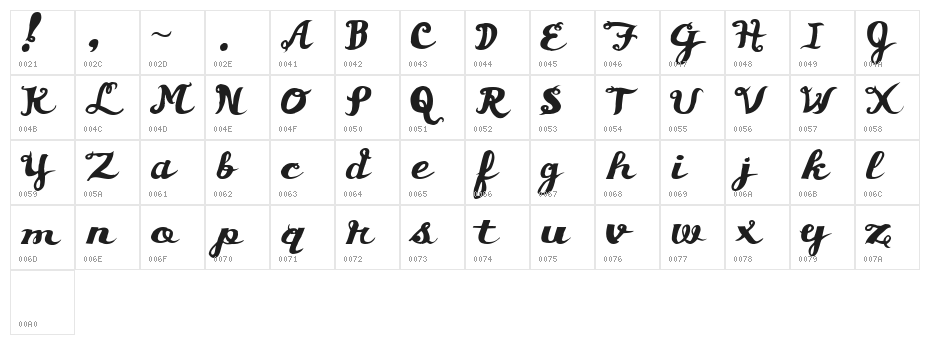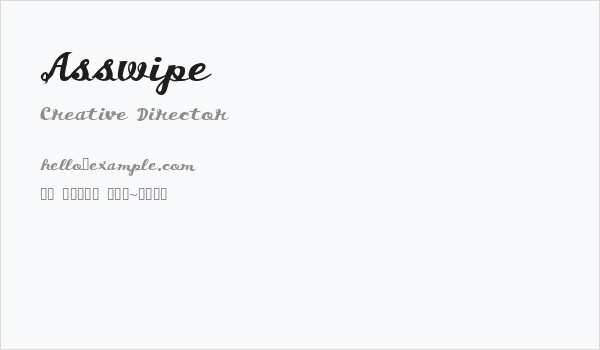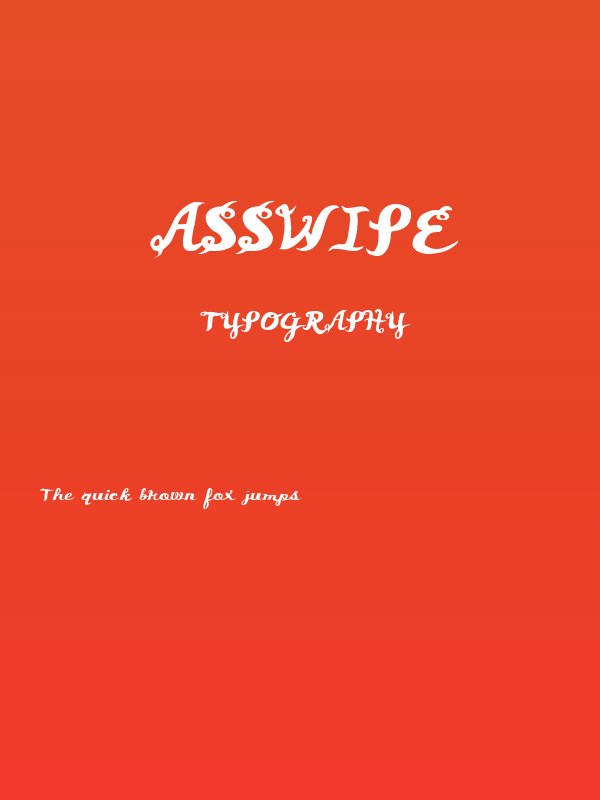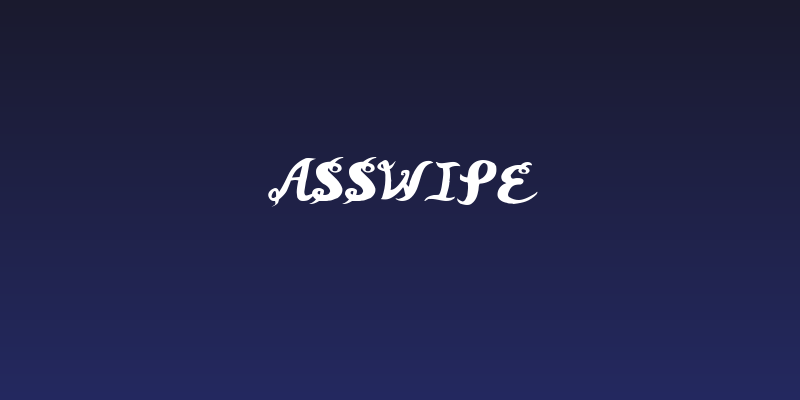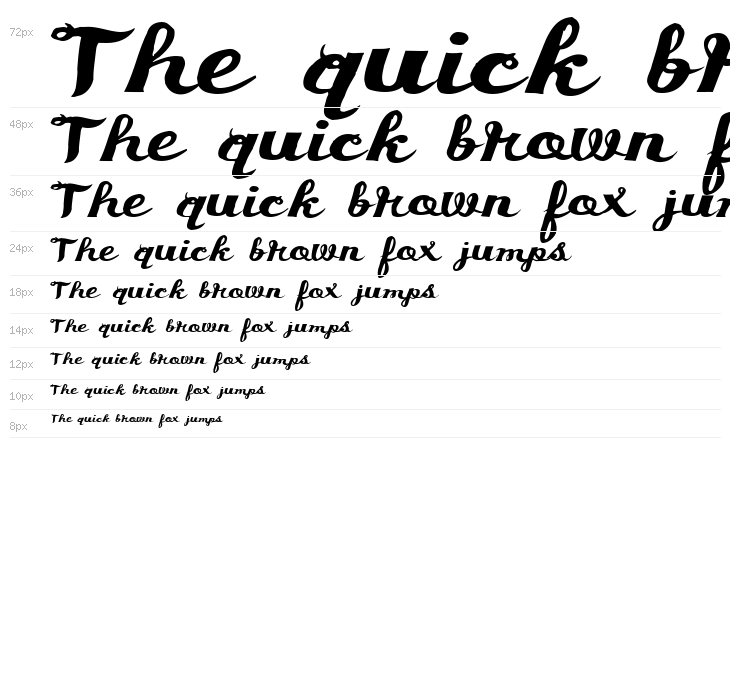
Asswipe Font
| Caso d'uso | Logos, Invitations, Decorative headings |
| Progetti proposti | Ideal for wedding invitations, formal event programs, and luxury brand logos. |